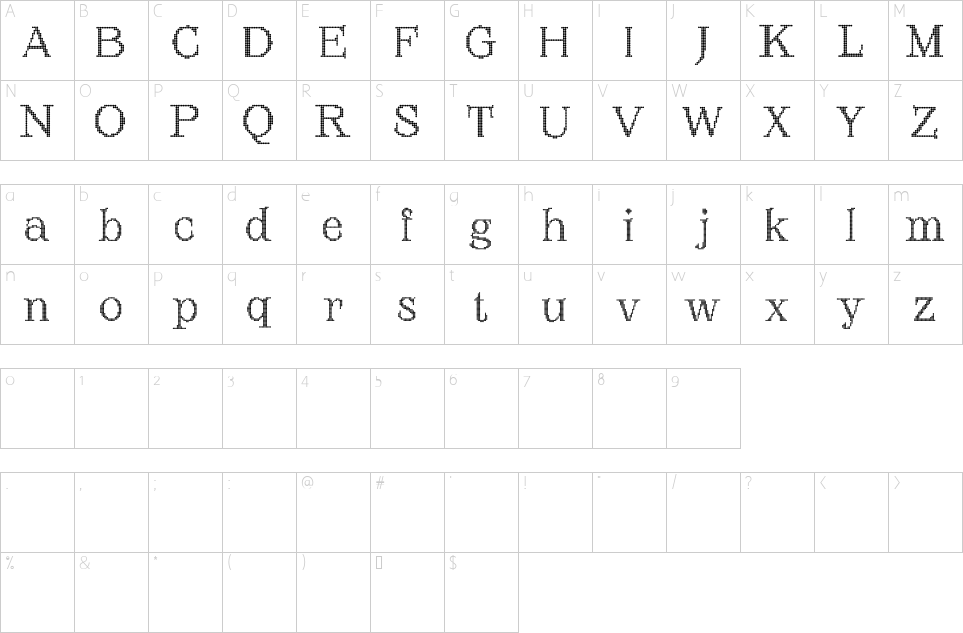
A Alfena Disco é uma fonte originalmente criada pela Craft Supply Co, disponível gratuitamente tanto para Windows quanto para Mac. Este estilo dinâmico e vibrante traz uma sensação ativa e alegre, adequado para qualquer aplicação que valorize uma aparência moderna e divertida. Com sua design característico, a Alfena Disco se destaca em qualquer projeto de design, seja para criar identidades digitais, materiais de marketing ou até mesmo para personalizar mensagens online. Seja você um designer gráfico profissional ou iniciante, esta fonte é perfeita para se tornar uma parte integrante do seu kit de ferramentas. Com apenas 178 downloads, é um raro tesouro digital que vale a pena ter em sua coleção. Não perca esta oportunidade de trazer um toque único e vibrante a seus projetos.